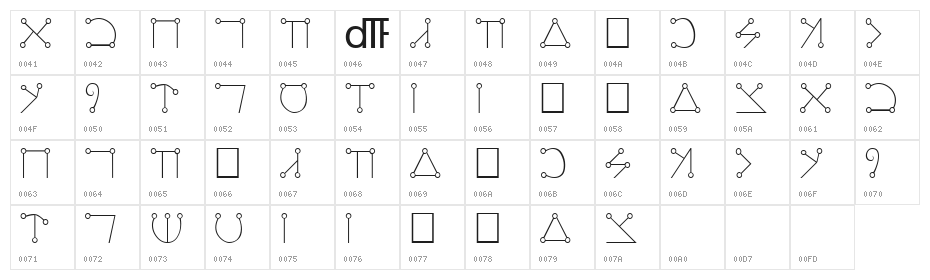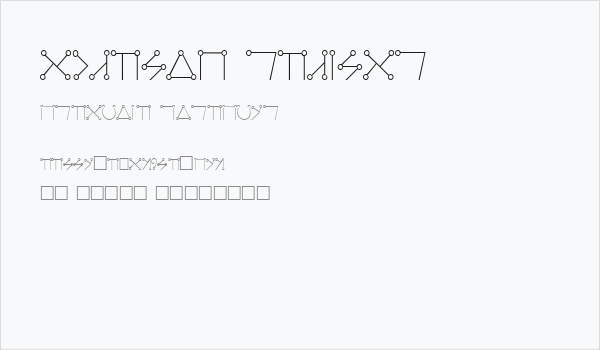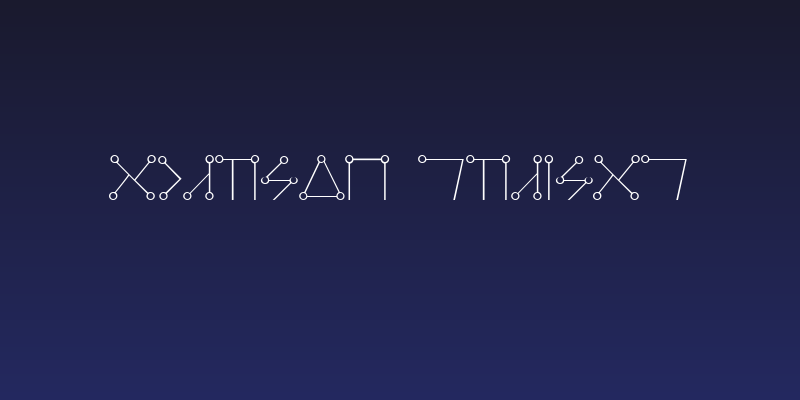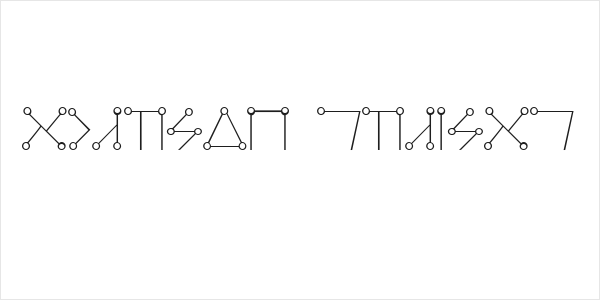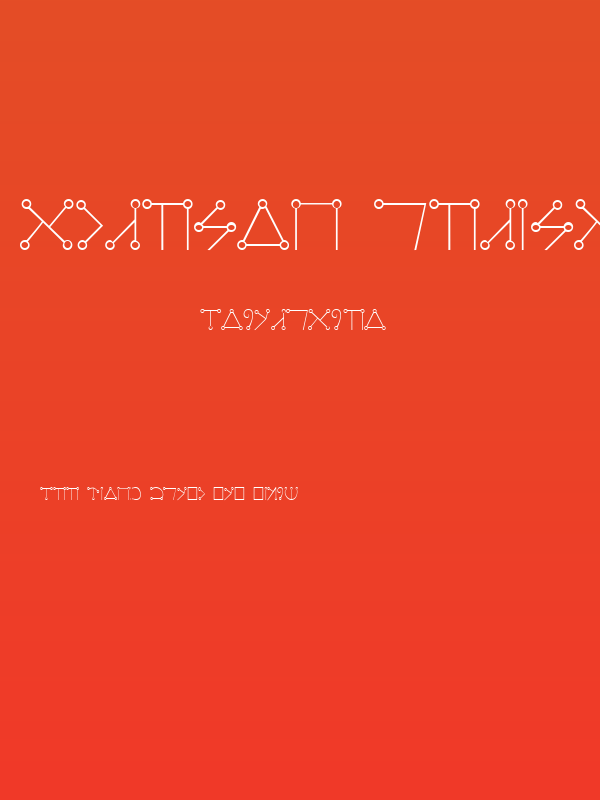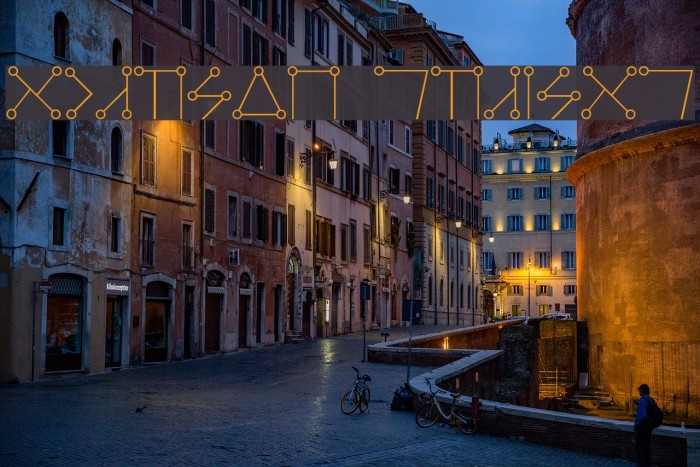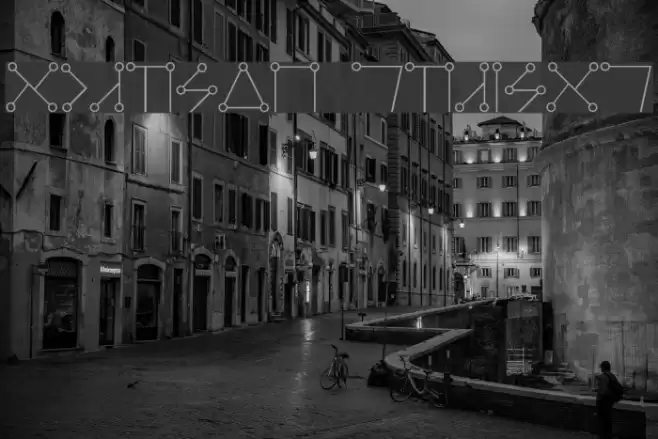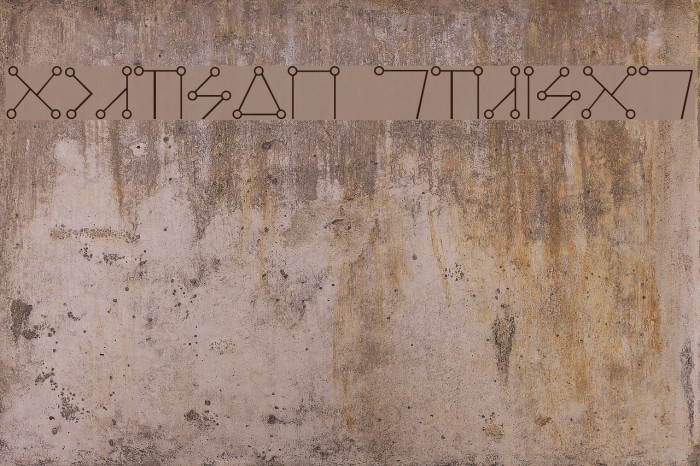
Angelic Regular Font
| Stil general | Modern, Futuristic |
| Caz de utilizare | Logos, Posters, Artistic Designs |
| Proiecte propuse | Ideal for sci-fi themed designs, artistic posters, digital art projects, and modern branding. |